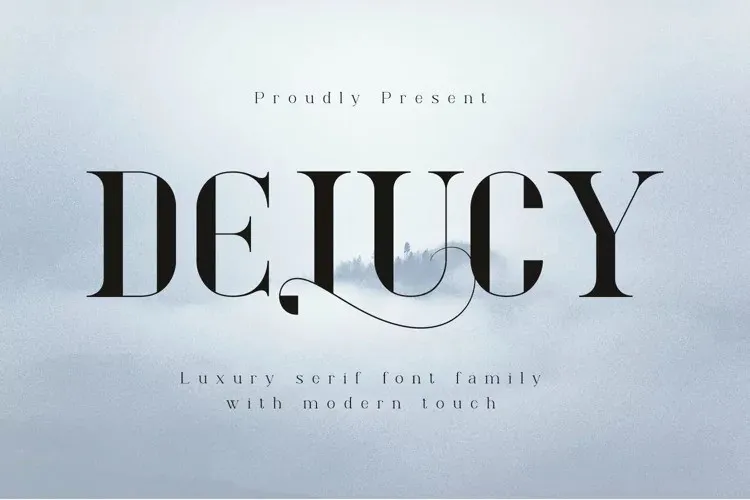
A Delucy Font é uma elegante e moderna fonte serif produzida pelo designer Irfan Hidayat. Ela possui um equilíbrio entre masculino e feminino, oferecendo uma versatilidade que a torna perfeita para projetos de design tanto grandiosos quanto sutis. Este conjunto sofisticado de letras proporciona uma presença visual única, capaz de dar vida à qualquer projeto de identidade visual ou tipografia em geral. Seja você um profissional de arquitetura, designer gráfico, designer web ou criativo de mídia social, a Delucy Font tem o poder de transformar suas criações em algo extraordinário e único. Com seu design refinado e sua versatilidade, ela certamente se encaixa perfeitamente na categoria das fontes serif do 99designs.